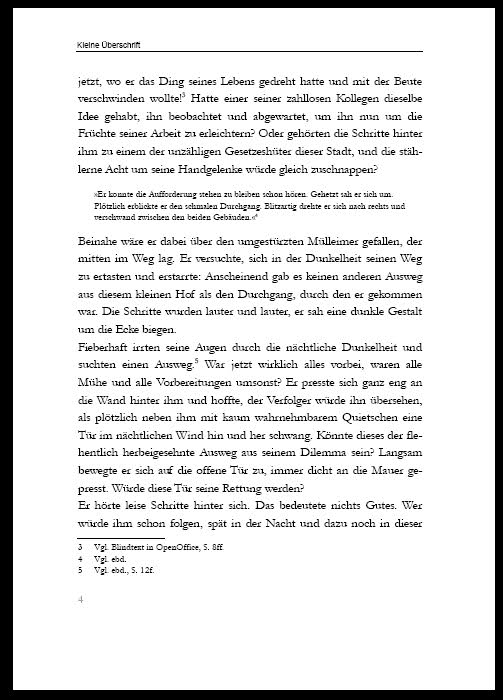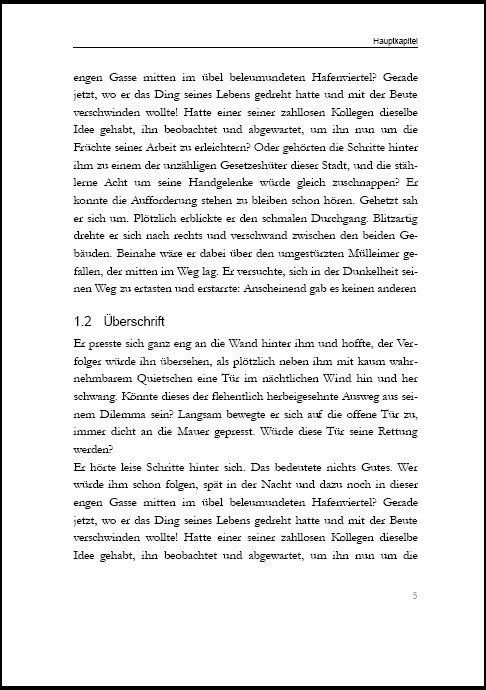
für folgendes Textformat in OpenOffice 2.4 möchte ich gerne einen typographisch möglichst ansprechenden Zeilenabstand einstellen:
Seitenformat: A5
- Rand innen: 2,20 cm
- Rand außen: 1,50 cm
- Rand oben: 1,80 cm
- Rand unten: 1,80 cm
Schriftart: Times
Schriftröße: 10 pt
Bei diesen Einstellungen komme ich auf gut 60 Zeichen pro Zeile.
Nun habe ich mal das Schriftbild mit drei verschiedenen Einstellungen für Zeilenabstände verglichen:
- Proportional: 120 %
- Durchschuss: 2 pt
- Fest: 12 pt
Der Zeilenabstand bei "Proportional" und "Durchschuss" ist sehr ähnlich (bei Durchschuss etwas kleiner als bei Proportional). Ein weiterer geringfügiger Unterschied ist, dass nach Absätzen der Zeilenabstand beim Durchschuss minimal größer ist als im Fließtext.
Mit der Einstellung "Fest" 12 pt sind die Zeilen deutlich enger aneinandergerückt - auf den ersten Blick fand ich, sah es ganz ordentlich aus, auf den zweiten Blick aber eher nach Bleiwüste...
Auch wenn es hier also "nur" um Fragen des ästhetischen Empfindens geht wäre es klasse, wenn der eine oder andere Typographie-Experte mal seine Meinung zur optimalen Einstellung des Zeilenabstandes im genannten Fall mitteilen könnte.
ohne eine Schrift zu nennen, kann man das schlecht beurteilen. Zeige doch einfach eine Musterseite - das geht viel schneller. :-)
Hast Du in irgendeiner Form mir Grafiken, Formeln oder jeglichen anderen Objekten zu tun, die größer sein könnten als die eigentliche Texthöhe? Wenn das der Fall ist, dann solltest Du von »Fest« die Finger lassen; das schneidet Dir nämlich im Zweifelsfall die Objekte oben einfach auf Texthöhe ab bzw. es kommt zu Kollisionen zwischen Objekt und Text. Wenn es wirklich nur Fließtext ist, dann spielt es eher keine Rolle.
Als sehr grobe Faustregel für den Zeilenabstand kann gelten: Schriftgröße [pt] × 1,3. Das ist aber wirklich nur sehr grob; m.E. ist das z.B. für die Palatino zu viel und für die Leitura viel zu wenig. Mit 120% liegst Du bei der Times nicht gar zu falsch aber meiner Erfahrung nach hilft, gerade bei der Times, tatsächlich fast nur eines: Druck mal eine Musterseite (Times in 10 pt) mit 11, 12, 13, 14, 15 und 16 pt Zeilenabstand. Je nach Seitenlayout geht es mir persönlich meist so, daß ich dann im Vergleich fast sofort sehe, welches die beste Lösung ist.
Also bei Times New Roman in 10 pt:
Durchschuss 2 pt
Proportional 120 %
Fest 12 pt
Bei OpenOffice kann ich im Menü Zeilenabstand nur zwischen folgenden Optionen wählen:
- Einzeilig
- 1,5-Zeilig
- Zweizeilig
- Proportional (Angabe nur in %)
- Mindestens (Angabe in pt)
- Durchschuss (Angabe in pt)
- Fest (Angabe in pt)
Wenn ich also mehrere Zeilenabstände ausprobieren soll (11 pt, 12 pt...) dann mit welcher Option?
Das ist ja im Grunde genommen egal, solange es sich um einen graduellen Anstieg handelt. Spontan würde ich in OO »Proportional« wählen und mich dann von 110% in 5er-Schritten aufwärts arbeiten. Du kannst alternativ auch unter »Tools – Options – OpenOffice.org Writer – General« die Einheit von cm auf pt umstellen. Allerdings sind die ZAB-Einstellungen in OO anders als in M$ Word. In Word erhalte ich, wenn ich Times in 10 pt setze, bei einem Zeilenabstand von 10 pt einen einfachen Zeilenabstand. In OO ist dies viel dichter, da berühren sich bei mir die Ober- und Unterlängen. Dementsprechend müßtest Du dann höhere Werte in pt wählen (so um 16 pt herum). Das mußt Du einfach ausprobieren.
Aber genau da liegt der Schatz begraben: Nimm einfach irgendeine Einstellung und fang mit Werten an, die für Dich ganz eindeutig zu eng bzw. ganz eindeutig zu weit sind und decke dann diesen Bereich in kleinen Schritten ab, ganz unabhängig davon, welche Einstellung Du letztlich wählst. Meist kommen dann nur zwei oder drei Ausdrucke in die engere Wahl; manchmal auch nur einer.
Hast Du in irgendeiner Form mir Grafiken, Formeln oder jeglichen anderen Objekten zu tun, die größer sein könnten als die eigentliche Texthöhe? Wenn das der Fall ist, dann solltest Du von »Fest« die Finger lassen; das schneidet Dir nämlich im Zweifelsfall die Objekte oben einfach auf Texthöhe ab bzw. es kommt zu Kollisionen zwischen Objekt und Text. Wenn es wirklich nur Fließtext ist, dann spielt es eher keine Rolle.
Das sieht nur auf dem Bildschirm abgeschnitten aus, beim Ausdruck ist alles ok.
Korrektur: Das gilt nur für Text, bei Bildern hast Du recht.
Ergänzung: Wenn man den Zeilenabstand nicht auf fest stellt, kriegt man irgendwann Probleme mit der Registerhaltigkeit. Außerdem kann es dann passieren, dass irgendwo mitten in einem Absatz zwei Zeilen weiter auseinander rutschen, wenn beispielsweise eine Indexziffer in der Zeile steht.
Außerdem kann es dann passieren, dass irgendwo mitten in einem Absatz zwei Zeilen weiter auseinander rutschen, wenn beispielsweise eine Indexziffer in der Zeile steht.
Von der Ästhetik her, ist sie mir zu sehr "ziselierte Buchschrift", ich denke du benötigst etwas stabileres.
Zudem ist eine Garamond nicht gleich einer Garamond, dort tummelt sich wirklich unterschiedliches unter diesem Bezeichner. Deine Garamond 3 unterscheidet sich beispielsweise sehr von der Adobe Garamond.
Kostenfrei, der ITC Charter ähnlich, mein Vorschlag: Charis SIL. Die dann auch bei kleiner Schrift solide steht.